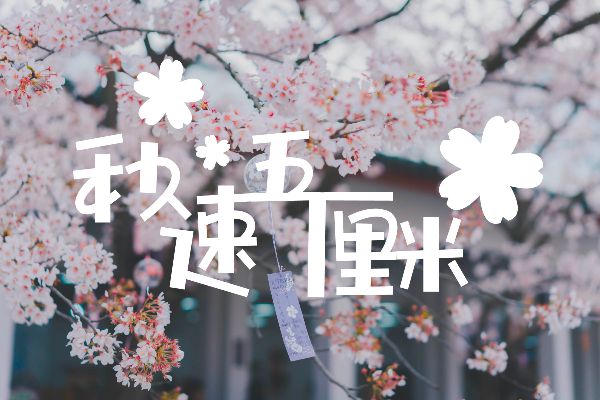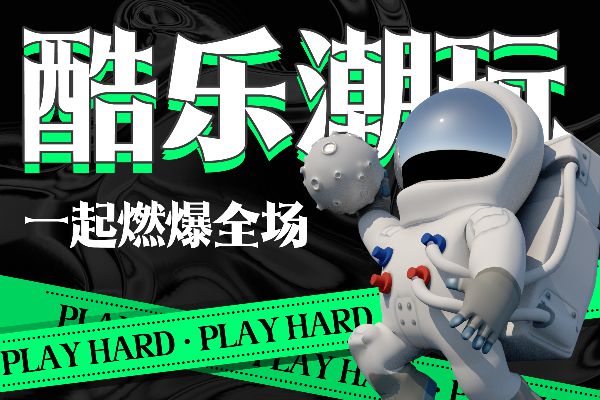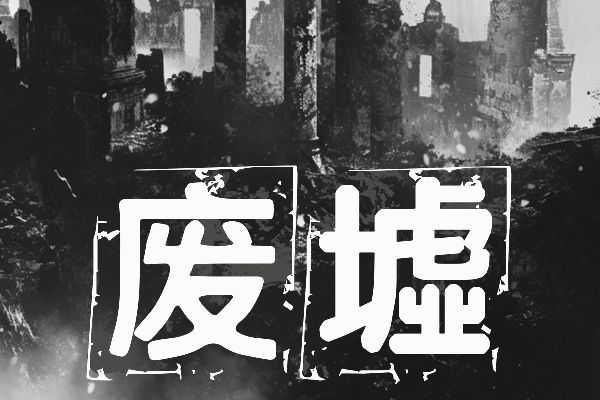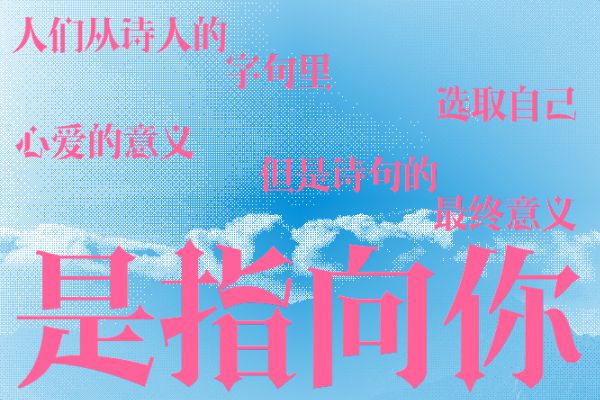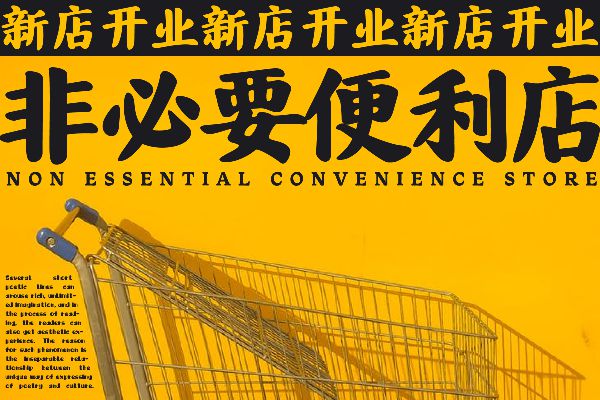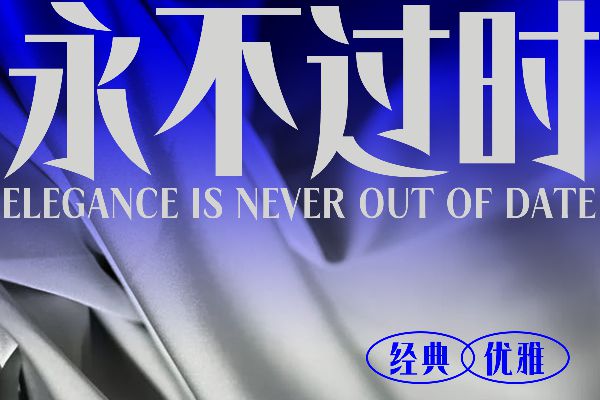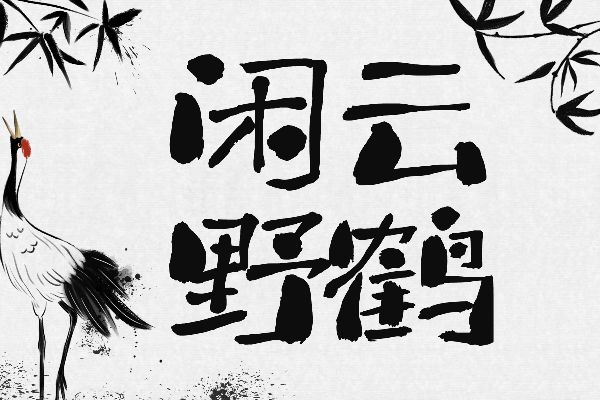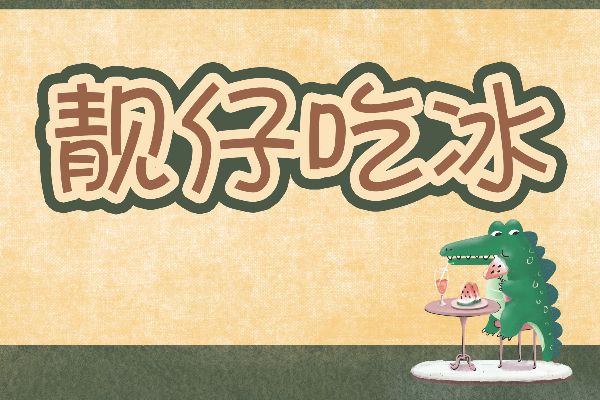
Aa字库—为小可爱们用字而努力奋斗。2015年Aa字库创立,在北京、深圳均设立团队,开始原创设计风格独树一帜的版权字体。截止目前共拥有版权中西文字库1000余套,其中方萌、甜甜圈、极细黑、元气满满等为代表的创意字深受用户喜爱。2018年Aa字库首创安卓手机系统彩色字在各个合作平台上线,引领个性化字体潮流,被华为等多个合作方评为优秀字体合作伙伴,在各大平台深受用户欢迎。